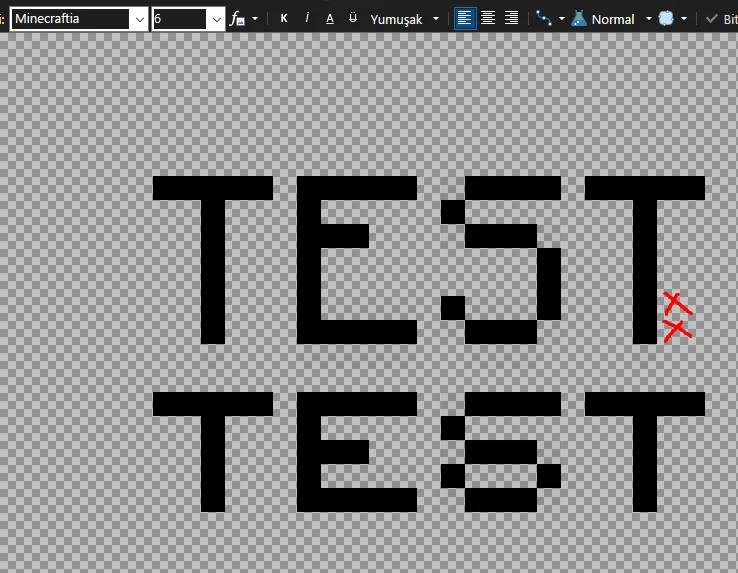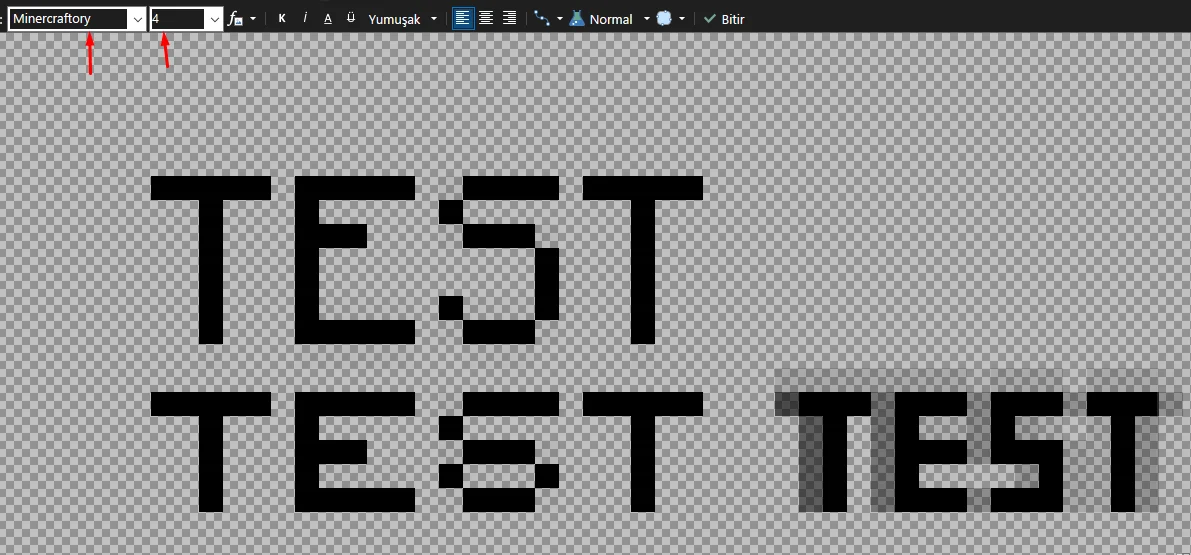
Çözüldü Rank tasarımı için font önerisi
Merhabalar, sunucum için custom rank tasarımları yapıyordum. Her şey tamam ama tek sıkıntım şu an font, düzgün bir font bulamıyorum. Ya çok ince oluyor ya da tam uymuyor. Öneriler yaparsanız cidden çok sevinirim.
ben genelde küçük font kullanıcaksam minecrafttia kullanıyorum ve daha da küçültmek için altdan 2 sırasını kesip yukarı kaydırarak yapıştırıyom :D çözülüyo sorun deneyebilirsin.
mantıklıymış hocam deniyebilirim bu arada bildiğiniz bold olarak pixel fontlar var mı ve şu tarzda bir font bulabilsem iyi olurdu
uğraştırır biraz bu ama bu font ile yapılabiliyo tabi yandaki gölgeleri kendin yapmalısın